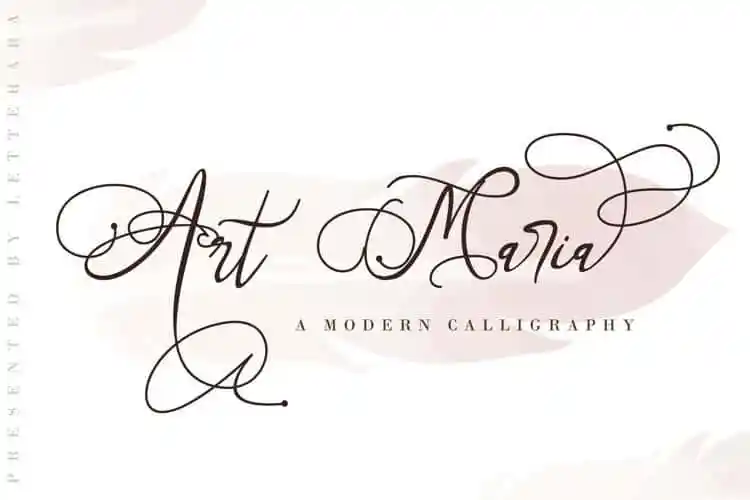
Art Maria Calligraphy Font – Download Grátis
A Art Maria Calligraphy Font foi projetada a partir de escrita a mão, oferecendo um estilo de caligrafia moderno e único que mantém seu naturalismo vibrante. Este recurso é perfeito para quem busca uma fonte que não apenas adiciona sofisticação aos design projectos, mas também realça a elegância das letras em qualquer trabalho gráfico. A fonte oferece um conjunto completo de caracteres alternativos e recursos OpenType, permitindo que designers criem designs com um toque refinado e distintivo. Com o formato Art Maria, você terá uma ferramenta poderosa para transformar os textos mais simples em obras de arte.